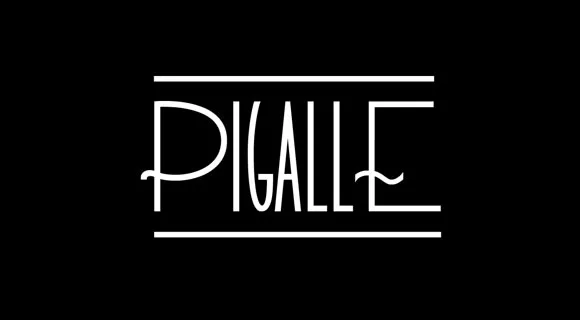
Rispa Typeface é uma elegante tipografia regular que oferece uma vibe nostálgica para os projetos modernos e sofisticados. Inspirada no design retro dos anos 80, essa fonte é perfeita para estampas de tênis, desenhos em camisetas personalizados e criações digitais inspiradas na década passada. Ela também pode ser usada livremente tanto para fins pessoais quanto comerciais, tudo isso graças ao talento do designer Hamilton. Se você está procurando por uma fonte que combine ar saudosismo com simplicidade moderna, Rispa é a escolha certa. Para mais detalhes sobre o trabalho do autor, visite o site de Hamilton em http://www.hamilton.com.br/. Ali, você encontrará inspirações e recursos para projetos futuros baseados nas habilidades criativas dele.